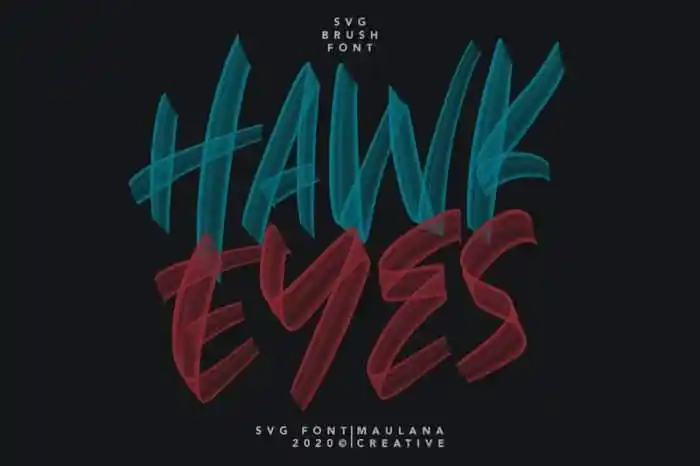
Hawkeyes Brush Font – Download Grátis
A Hawkeyes Brush Font é uma deliciosa tipografia script que traz a autêntica sensação de arte feita à mão com uma esponja. Perfeita para personalizar seus designs, esta font foi criada pelo talentoso designer Maulana Creative em 99designs. Suavemente adaptável a várias aplicações, ela está perfeitamente adequada a criação de assinaturas, cartões de selo, logotipos, texturas tipográficas, capas de livros ou revistas, cabeçalhos de websites, folders, roupas de marca, embalagens e até mesmo materiais de divulgação. Seja você um designer de moda, editor de revistas, produtor de conteúdo online ou criador de campanhas de marketing, a Hawkeyes Brush Font trará uma textura única e encantadora à sua obra. Adquira-a agora para adicionar um toque personalizado e único ao seu trabalho!